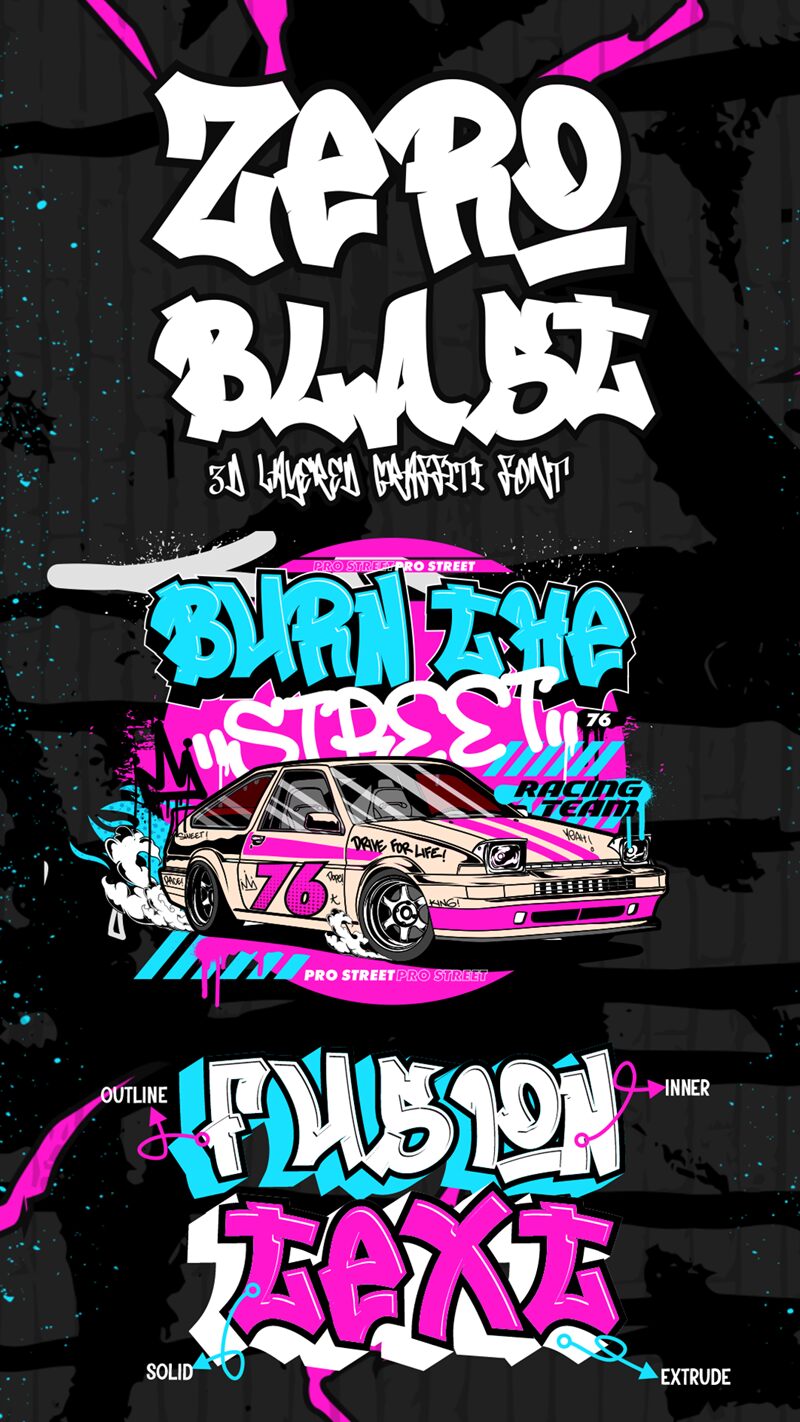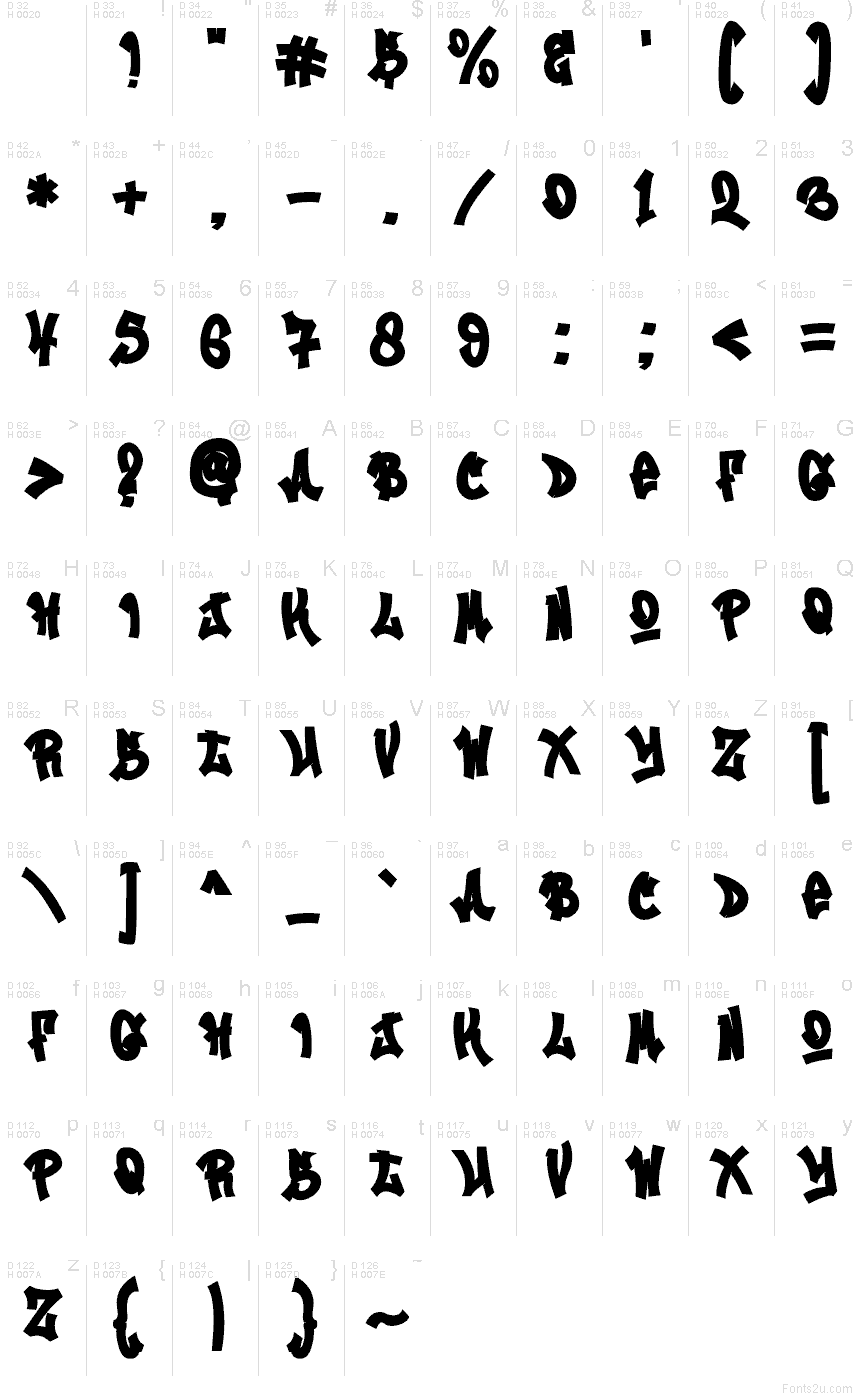
Il font Zero Blast Solid di Muhammad Panji Ramdhani (Sipanji x Figuree) colpisce con forme massicce e tratti spray che sembrano strappati direttamente da un graffiti urbano. Le lettere appaiono gonfie e piene, con bordi irregolari che creano istantaneamente movimento e carattere, anche nelle parole brevi. Come font graffiti gratuito, questa tipografia porta con sé una personalità decisa senza risultare illeggibile.
Utilizzare Zero Blast Solid su poster, copertine musicali, branding skate o streetwear, miniature per giochi, header di YouTube/Twitch, adesivi e volantini per eventi conferisce al tuo messaggio una voce cruda e ad alta energia. Questo font gratuito brilla anche negli annunci social e negli slogan per il merchandising. Prova ad abbinare la famiglia Zero Blast con una sans serif condensata e pulita per i dettagli, e dai spazio ai titoli: nelle dimensioni grandi, quei tagli netti esprimono al meglio il loro potenziale.